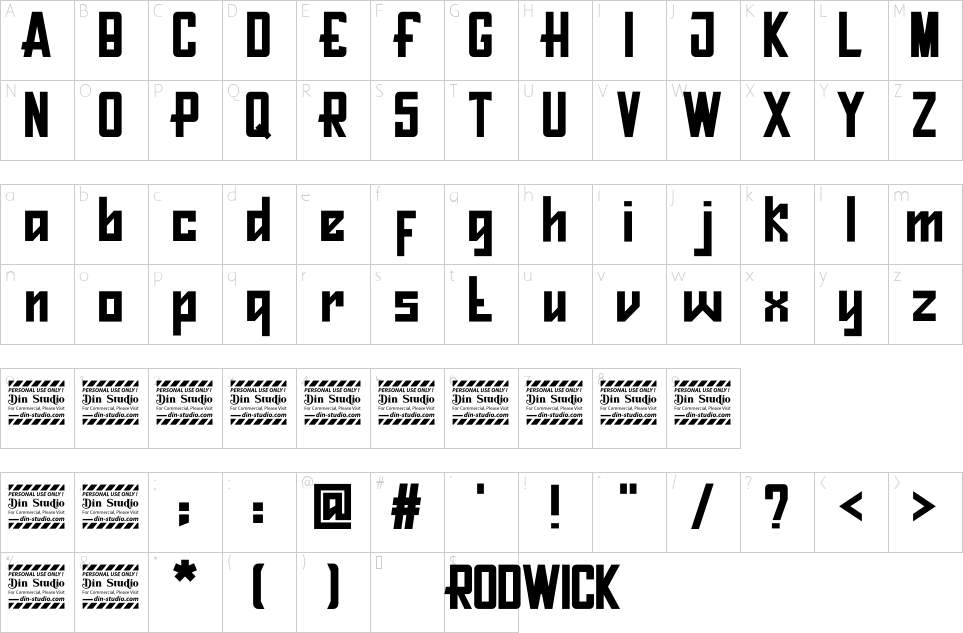
Descubra a elegância arquitetônica e a simplicidade moderna da Rodwick Font para suas próximas criações visuais com esta linda fonte gratuita. Desenvolvida pela Din Studio, a Rodwick traz uma combinação perfeita de facilidade de uso e design cuidadosamente pensado, tornando-se um recurso valioso tanto para designers digitais quanto para criadores gráficos em geral. Sua arquitetura minimalista mantém o foco no texto, oferecendo uma excelente legibilidade e consistência ao longo de qualquer projeto. A versão gratuita da Rodwick é especialmente atraente para quem procura uma fonte moderna que seja fácil de se adaptar a diversos estilos de design. Com um download atingindo 13,724 vezes, pode-se inferir que muitos designers e criativos enxergaram em sua funcionalidade e estilo o que buscavam. A Rodwick oferece um ótimo equilíbrio entre simplicidade e força expressiva, tornando-a uma fonte ideal para aqueles que desejam adicionar um toque único ao seu trabalho. Descubra por si mesmo a beleza da Rodwick Font na sua próxima criação visual. Instale-a em seus projetos digitais ou impressos e veja como ela pode transformar suas ideias de design em realidade visível.